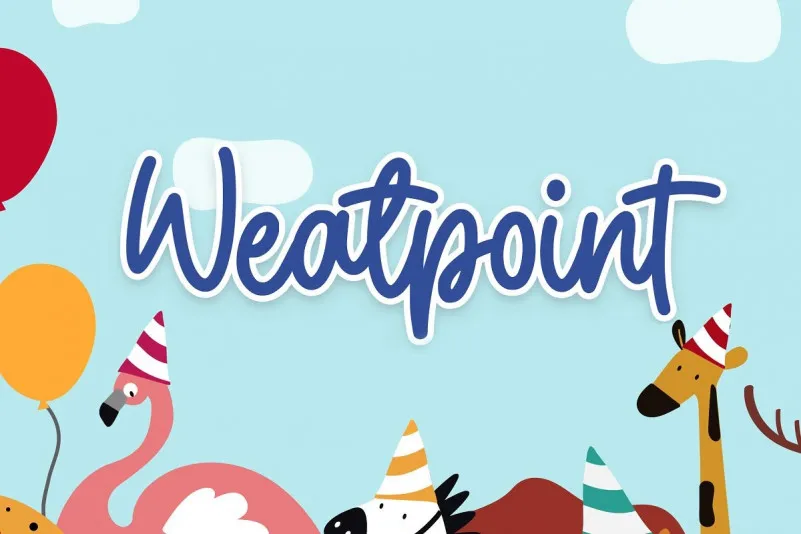
Weatpoint Script Font – Download Grátis
Esta é uma fonte desenhada para inspirar alegria, ideal para os produtos impressos destinados aos entusiastas do mundo infantil colorido e vibrante. Inspirada no divertido universo dos meninos e meninas, Weatpoint Font se destina perfeitamente para as criações de pessoas que apreciam o estilo infantil. Essa fonte foi criada por StringLabs e é especialmente concebida para aplicações como Kindergarten, festas de aniversário, personagens infantis, quadrinhos ou histórias em quadrinhos infantis, além do playground. Com sua variedade de estilos moderno, elegante, criativo, profissional e singular, essa fonte é perfeita para quem busca uma impressão única que seja autêntica e cheia de vida. Engane-se se pensar que isso não é a fonte ideal para o seu próximo projeto divertido!